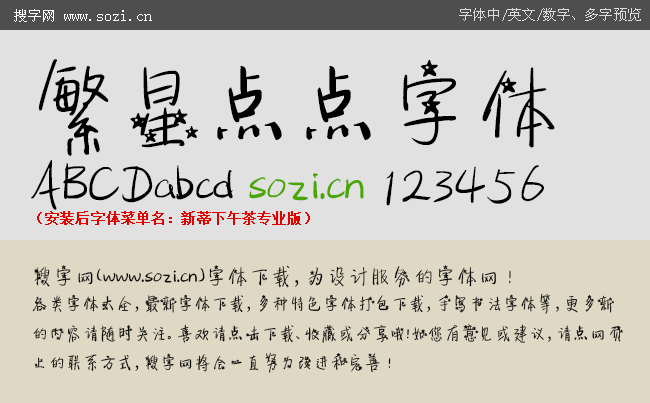
繁星點(diǎn)點(diǎn)字體
搜字網(wǎng)給大家提供一款書(shū)法風(fēng)格的字體下載。修改者給他起名為繁星點(diǎn)點(diǎn)字體,這款手機(jī)字體是以新蒂下午茶字體為原形,在字體周?chē)b飾上了可愛(ài)的星星圖案,新蒂下午茶字體是一款手寫(xiě)風(fēng)格的中文簡(jiǎn)體字體,非常有手寫(xiě)感,加入星星圖案后更加俏皮可愛(ài),喜歡的朋友可下載收藏。